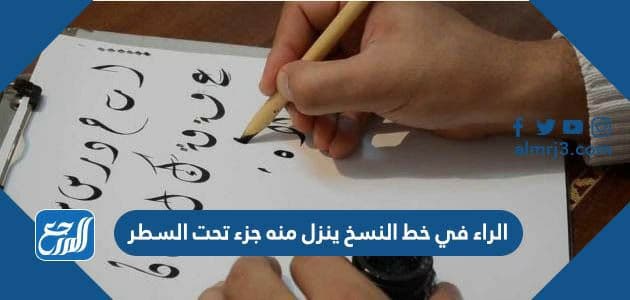
الراء في خط النسخ ينزل منه جزء تحت السطر
الراء في خط النسخ ينزل منه جزء تحت السطر هو ما سيتمّ الحديث عنه في هذا المقال، حيث يعدّ هذا السّؤال من الأسئلة الهامّة التي تتعلق باللّغة العربيّة، فقد كتب العرب اللّغة العربيّة بعدّة خطوطٍ وتنوّعت أشكال الحروف في كلّ خط، وعبر موقع المرجع سنتعرّف على كيفية كتابة حرف الراء في خط النسخ.
الخطوط العربية
تعدّ الخطوط العربية أو الخطّ العربيّ فنًّا من فنون الكتابة للكلمات أو الجمل، ولا تستخدم الخطوط العربيّة إلّا الأحرف الأبجديّة للغة العربيّة الثمانية والعشرين، وإنّ العامل الأساسيّ الّذي ساعد في اتّخاذ أحرف اللغة العربيّة أشكالًا عديدة، هو طريقة كتابتها، أي أنّ الحروف العربيّة في الكلمات والجمل لا تكتب مقطعةً بل متشابكة، ممّا أكسبها مرونةً وسهولةً لتشكيلها، وقد تطوّرت أشكال الخطوط والحروف عبر الزّمن حتّى وصلت إلى ما عليه الآن.[1]
الراء في خط النسخ ينزل منه جزء تحت السطر
سنوافيكم فيما يأتي بتصحيح العبارة الراء في خط النسخ ينزل منه جزء تحت السطر، وهذا السّؤال من الأسئلة الهامّة الّتي قد تُطرح على الطّلبة في مادّة اللغة العربية، والإجابة الصّحيحة هي:
- العبارة صحيحة.
فخطّ النّسخ واحدٌ من أروع الخطوط الّتي تُكتب فيها كلمات وجمل اللغة العربيّة، وهذه الخطوط قد اعتمدت على الكثير من القواعد الخاصّة الّتي تتكلّف بإعطائه الجماليّة الفنيّة والتّصميم الرّائع، وتنطلق هذه القواعد من خاصّية التناسب بين الحرف والنّقطة والدّائرة، ويعود أصل الخطوط العربيّة إلى الخطّ النبطيّ الّذي تم اشتقاقه عن الخطّ الآراميّ الذي كتب به العرب كتبهم ومؤلّفاتهم وتاريخهم، ومن أنواع الخطوط العربيّة خط النّسخ وخطّ الرّقعة والخطّ الأندلسيّ والخطّ الكوفيّ وخطّ الثلث والدّيوانيّ وغيرهم الكثير، ولا بدّ للعربيّ أن يتمسّك بلغته العربيّة وأن يتعلّم كيفية الكتابة بخطوطها المتنوّعة فهي جزءٌ لا يتجزّأ من تاريخه وثقافته وماضيه العربيّ العريق.[1]
خط النسخ
يعدّ أحد أكثر الخطوط استخدامًا في تاريخ الأمّة العربيّة والإسلاميّة، وهو أحد الخطوط الّذي يحمل جماليّةً خاصّةً ومميزةً عن غيره من الخطوط، وسمّي بخطّ النّسخ، لأنّ العرب قد استخدموه في نسخ الكتب والمؤلّفات وكتابتها في نسخٍ متعدّدة، وفي العصور الإسلاميّة الوسطى استخدم المسلمون خطّ النّسخ لكتابة آيات القرآن الكريم ضمن المصاحف، وقد تميّز خطّ النسخ بسهولة كتابة الأحرف وسرعة تشكيلها، ممّا أدّى إلى استعماله بكثرةٍ وانتشاره بشكلٍ واسع، كما قال الباحثون وأهل العلم أنّ له العديد من الأسماء كالبديع والمقور والمدوّر وغيرها.[2]
مميزات خط النسخ
توجد العديد من الخصائص الّتي تميّز خط النّسخ عن باقي الخطوط العربيّة وسنذكر فيما يأتي بعضًا منها:[3]
- يمتاز خطّ النسخ بجماليّته ووضوح كلماته وسهولة تركيب أحرفه وتشكيلها.
- يمتاز خطّ النسّخ بتساوي حجوم أحرفه.
- يمتاز خطّ النسخ بحفاظه على قواعد اللغة العربية.
- يمتاز خط النسخ بسهولة قراءة كلماته وجمله.
- يمتاز خطّ النّسخ بربطه بين الرصانة والبساطة.